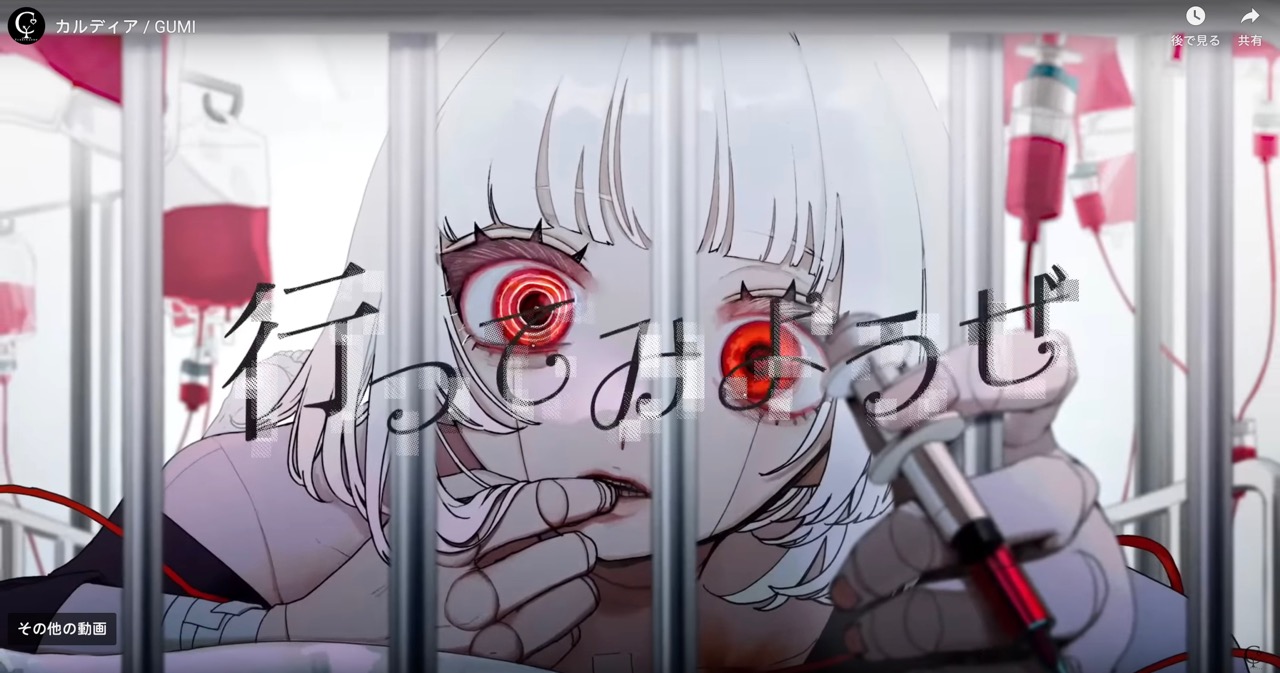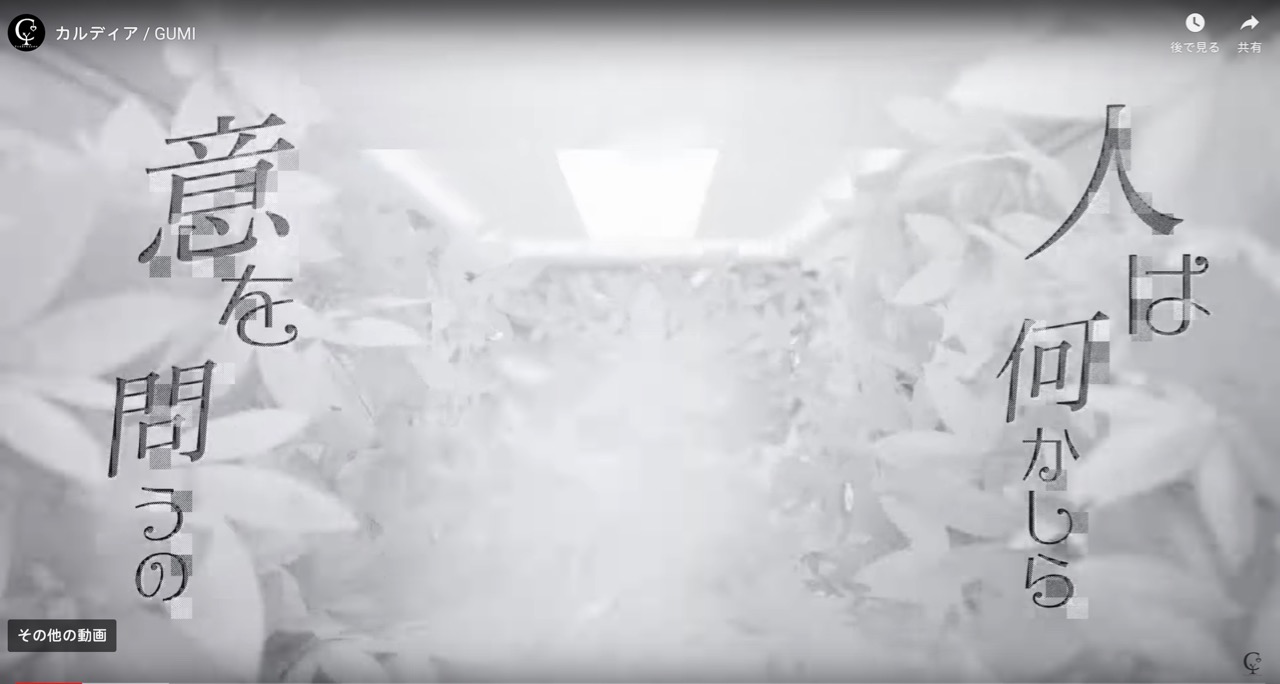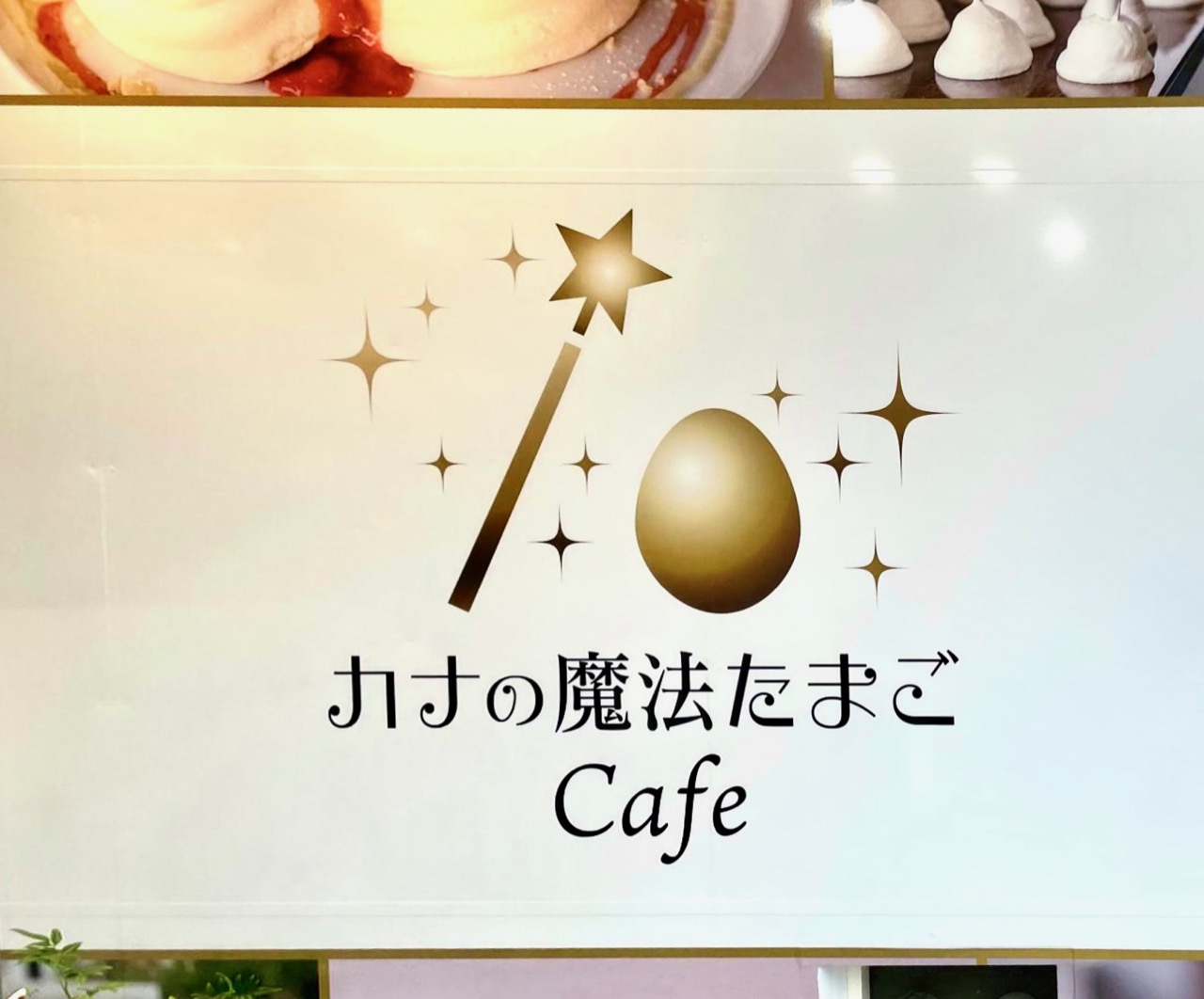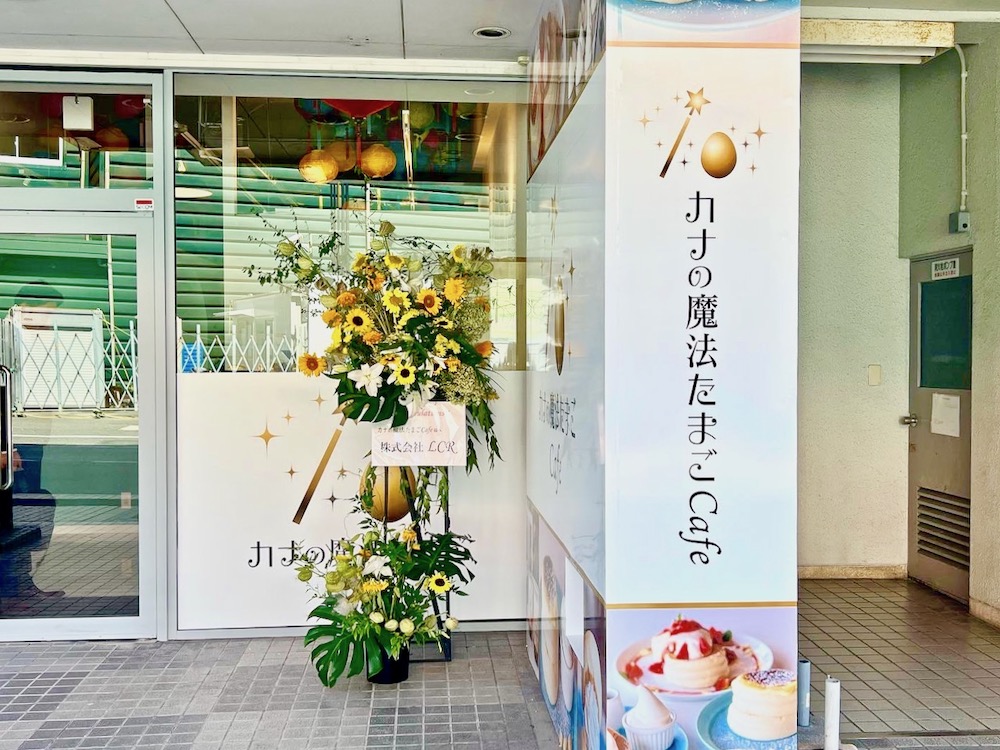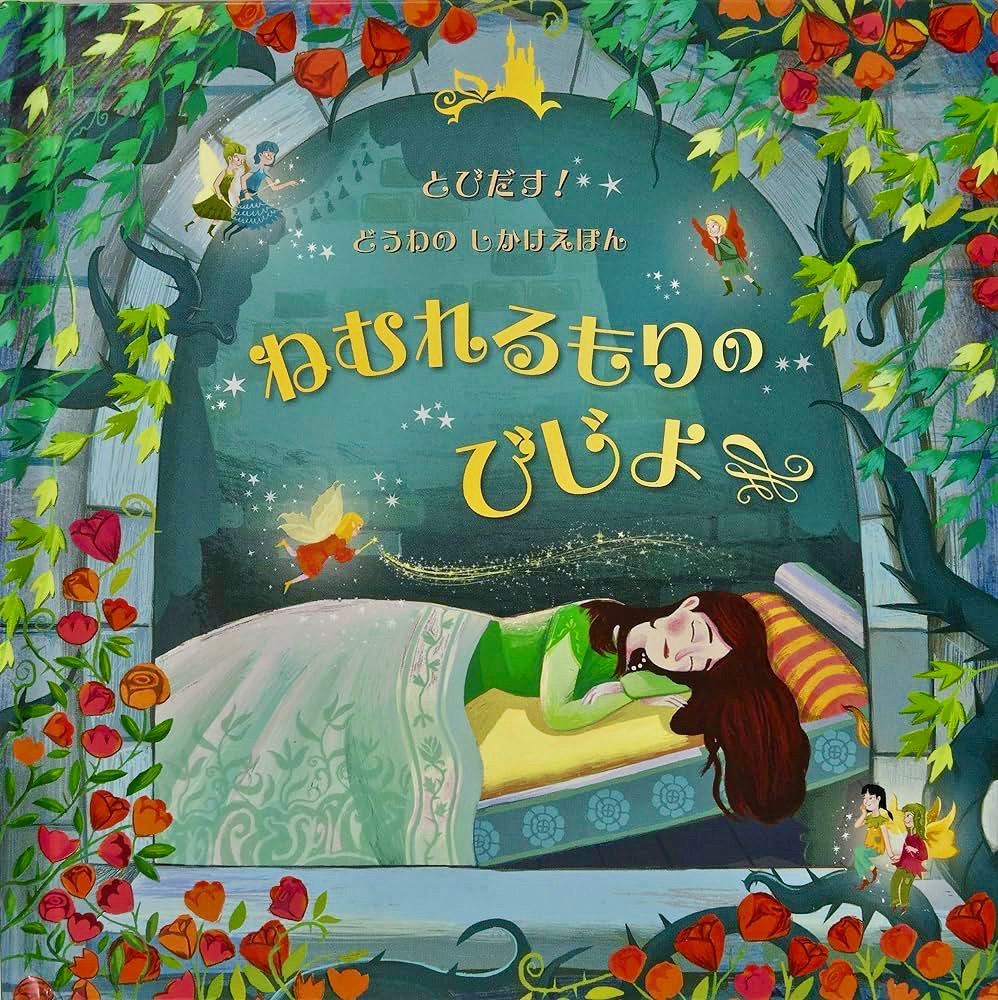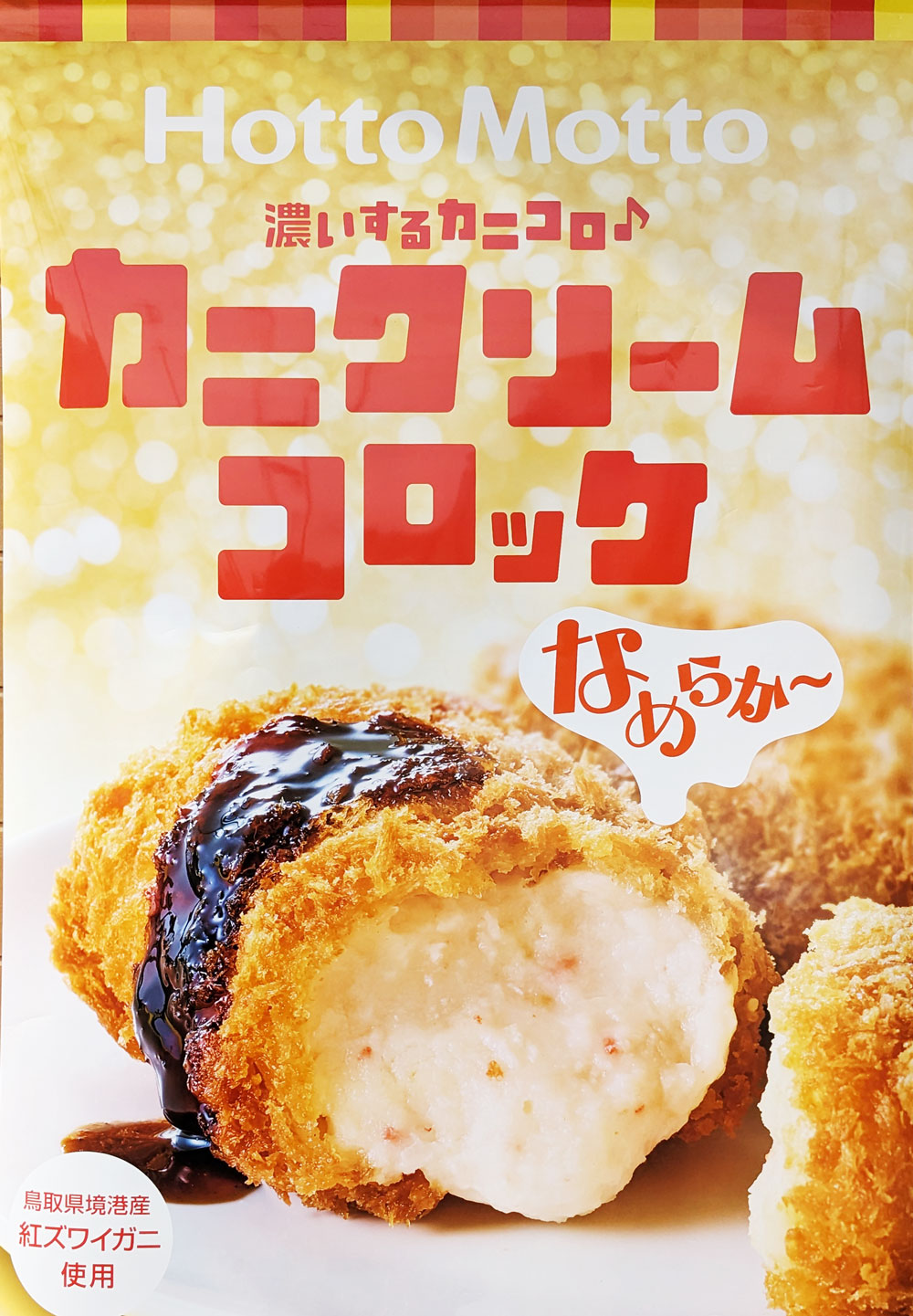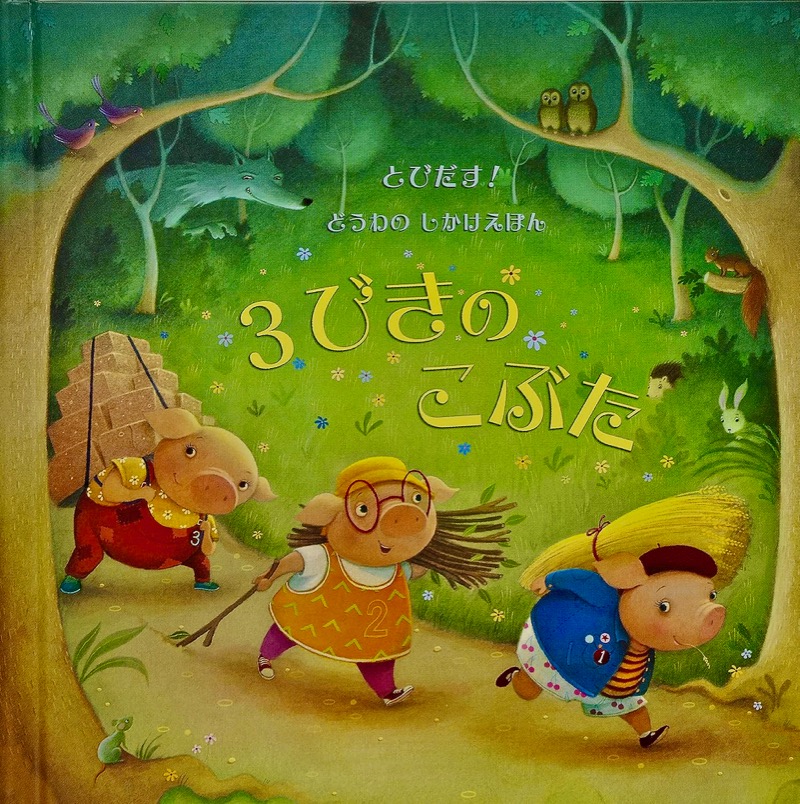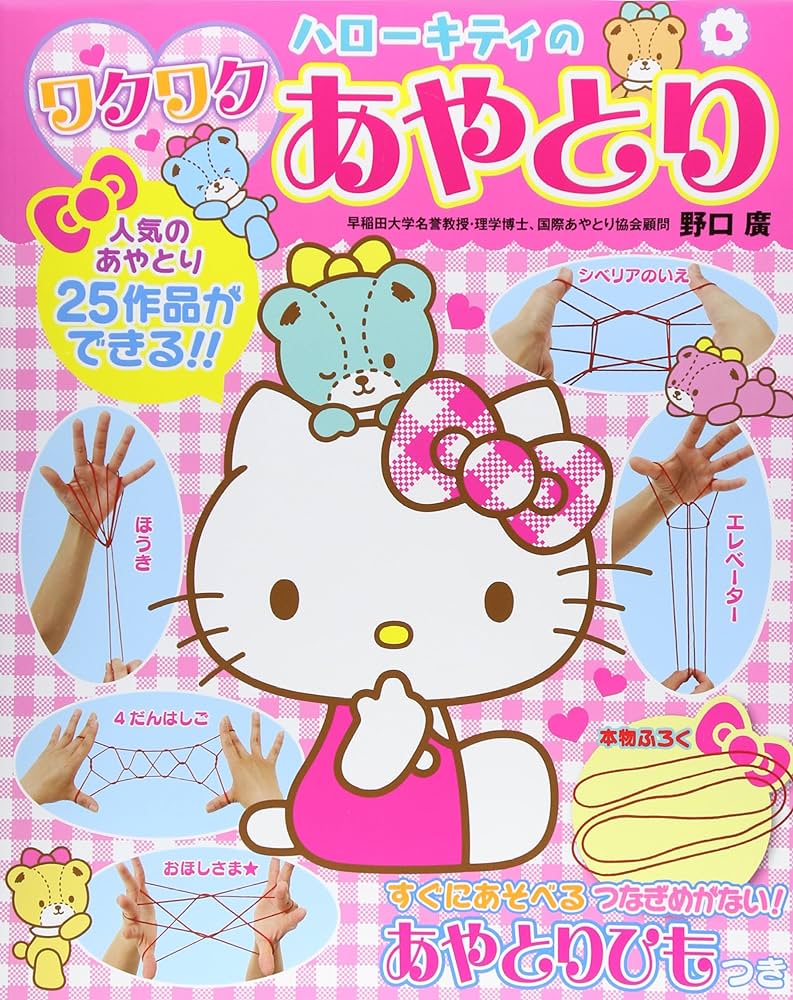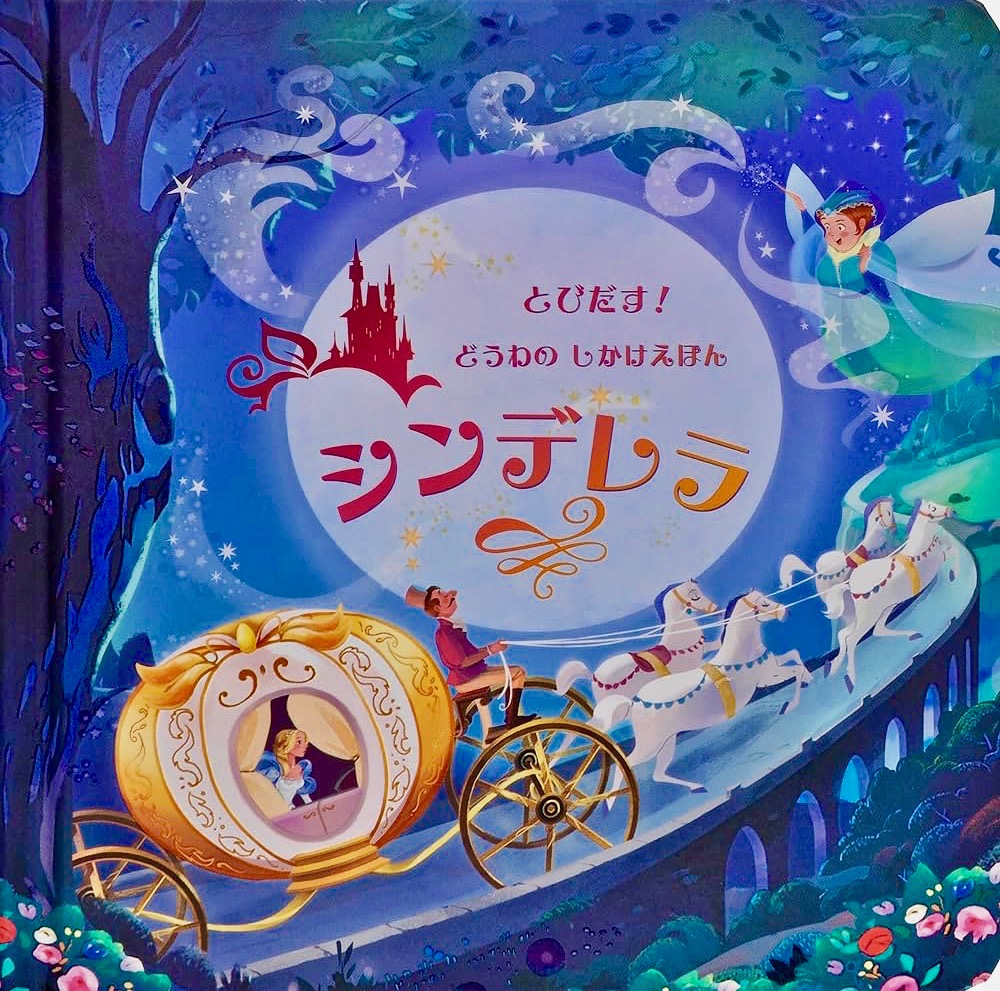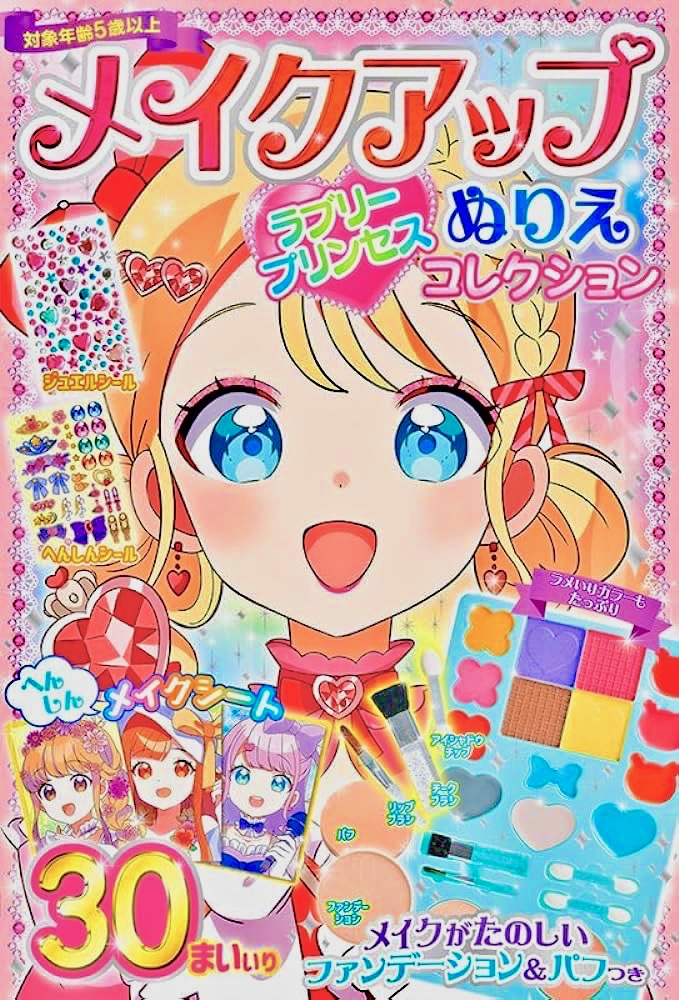
居酒屋のロゴ さとうゆたか
先日、大阪に行った時に見つけた居酒屋の看板。
すこし太く加工されている。
あ さとうゆたか
漢字書体が合っていないのが残念!
書名:そよ風のマリー
著者:飛鳥幸子
発行:立東舎
イベントのロゴ さとうゆたか
東京スカイツリータウン4Fの、スカイアリーナで催されているイベント。
クリスマスソング さとうゆたか
Christmas Lightsという素晴らしい曲です。
まだある。
もうひとつ。
本の表紙 さとうゆたか
書名:トリックアートサンタクロース
著者:北岡明佳 監修/グループ・コロンブス 構成・文
発行:あかね書房
パン屋さんのロゴ さとうゆたか
土曜日に放送されている、テレビ朝日の「人生の楽園」。
12月6日に放送された八戸のパン屋さんのロゴに使われていた。
シール帳? さとうゆたか
ダイソーで売っていたもの。
本の表紙 さとうゆたか
書名:トリックアートハロウィーン
著者:グループ・コロンブス、北岡明佳(監修)
発行:あかね書房
アニメの劇中 takumi
放送中のアニメ「野原ひろし 昼メシの流儀」。
劇中でえれがんとフォントが使われていました。
もう1枚。
テレビ番組 さとうゆたか
テレビ朝日系列の「激レアさんを連れてきた。」
動画のエフェクト処理で文字がすこし歪んでいる…。